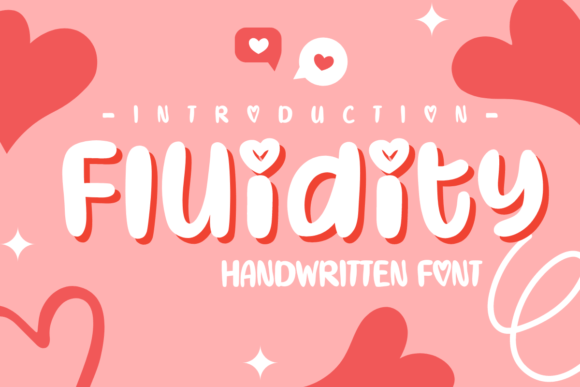
Fluidity Font
اكتشف Fluidity Font، الخط العصري الذي يجمع بين الأناقة والانسيابية ليمنح تصاميمك لمسة فريدة ومميزة. يتميز هذا الخط بتفاصيله المتقنة وانحناءاته الناعمة التي تجعله مثالياً للمشاريع الإبداعية، مثل الشعارات، والتصميمات الطباعية، والهويات البصرية، وتصميمات السوشيال ميديا.
✨ مميزات الخط:
✔ تصميم أنيق ومتوازن يناسب مختلف الاستخدامات
✔ يدعم الحروف الكبيرة والصغيرة بتنسيق احترافي
✔ مثالي للتصميمات الرقمية والمطبوعة